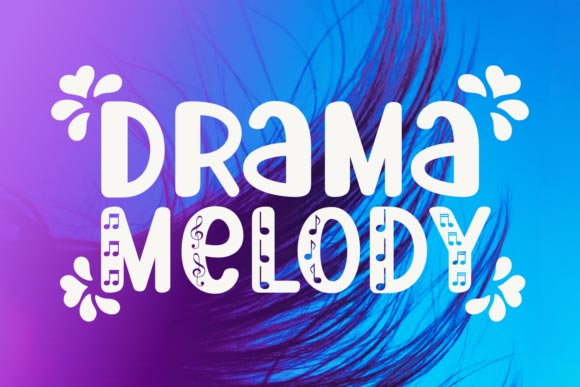
دانلود فونت انگلیسی فانتزی و حرفه ای Drama Melody
درام ملودی یک قلم نمایش اصلی و زیبا است. این شامل یک نسخه موسیقی با موسیقی است که پروژه های هنری خود را به سطح بعدی می برد! از جذابیت های منحصر به فرد خود الهام بگیرید و کارتهای تبریک شگفت انگیز ، آرم ها ، لوازم التحریر و چیزهای دیگر ایجاد کنید!
Drama Melody is an original and cute display font. It includes a musical-themed version that will take your crafting projects to the next level! Get inspired by its unique charm and create amazing greeting cards, logos, stationery and much more!